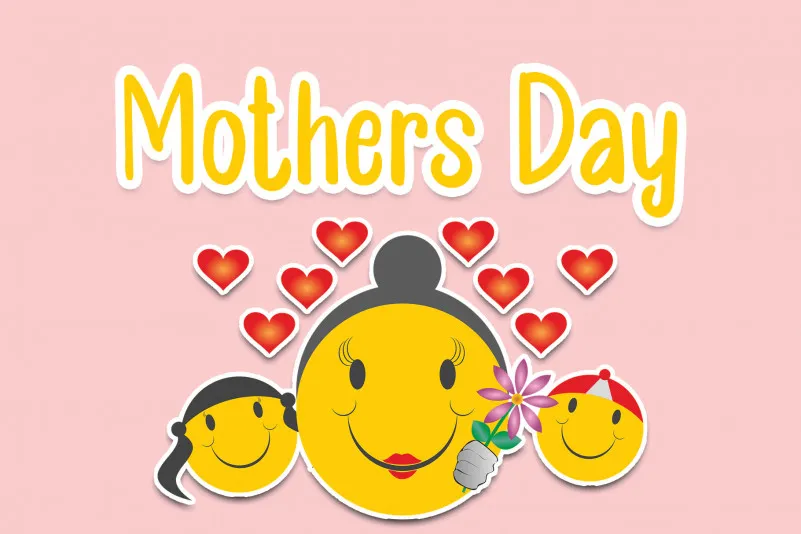
Mothers Day Font – Download Grátis
Esta é uma fonte feita à mão que traz divertimento e vivacidade. Ela tem um ar limpo e com um toque engraçado, fazendo-a perfeitamente adequada para todos os seus logotipos, marcas, redes sociais e projetos casuais de DIY. O Mothers Day Font é uma fonte perfeita para aqueles dias especiais dedicados às mães, mas também se destina a qualquer ocasião que exija um toque de personalização. Seja em sua camiseta personalizada ou no banner da sua festa de aniversário da mãe, esta fonte será uma escolha ótima para deixar seu trabalho ainda mais especial.